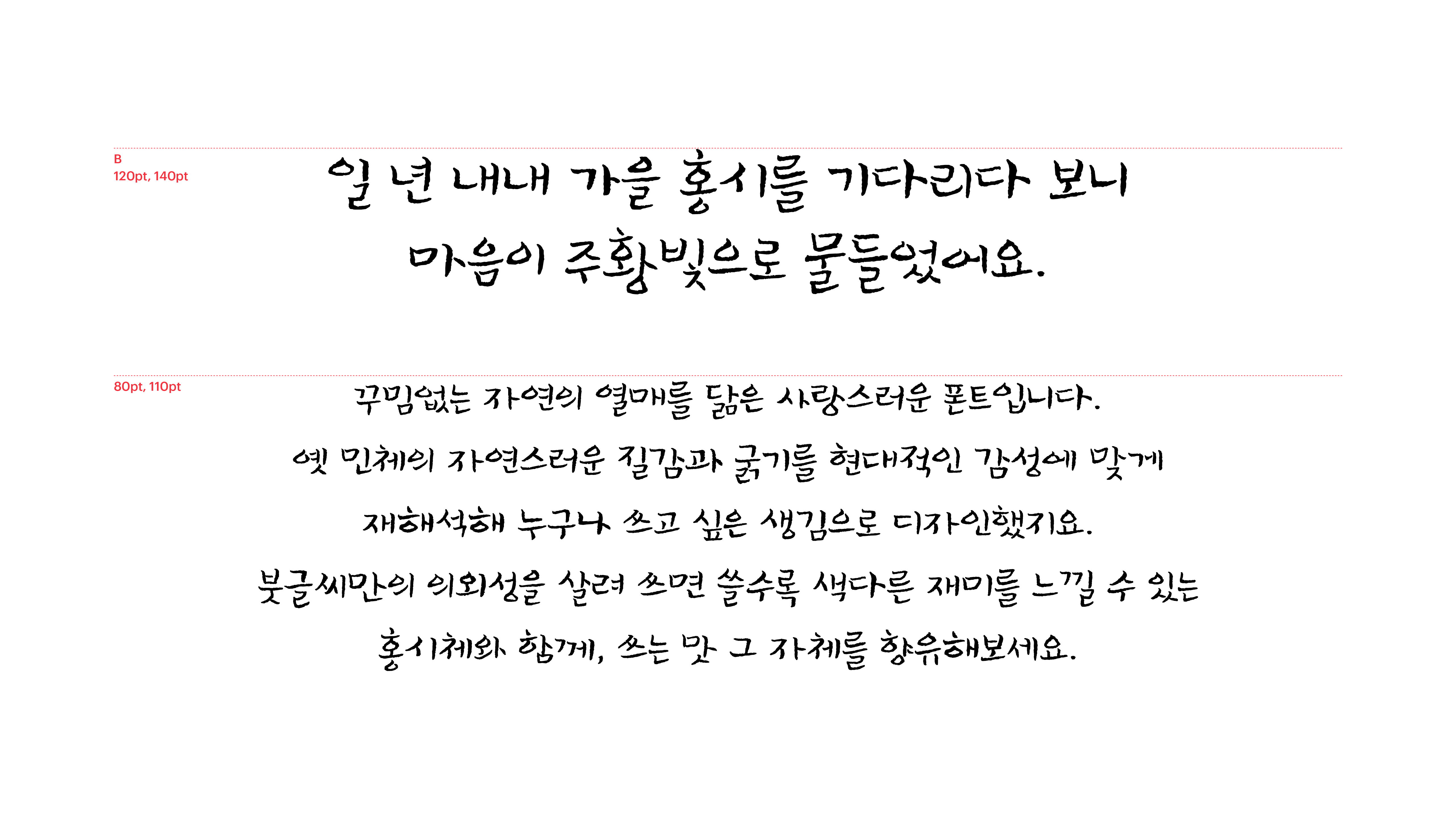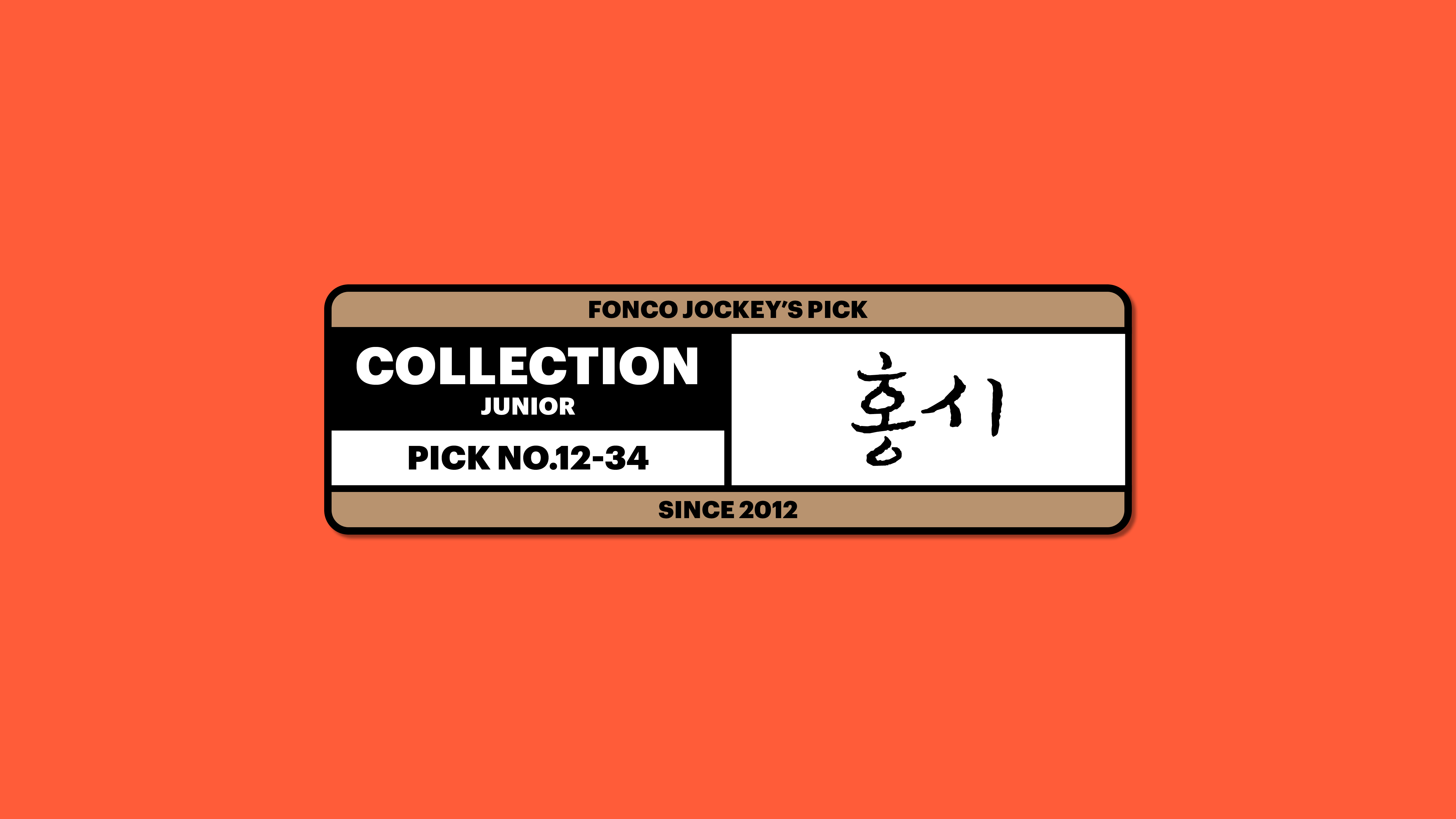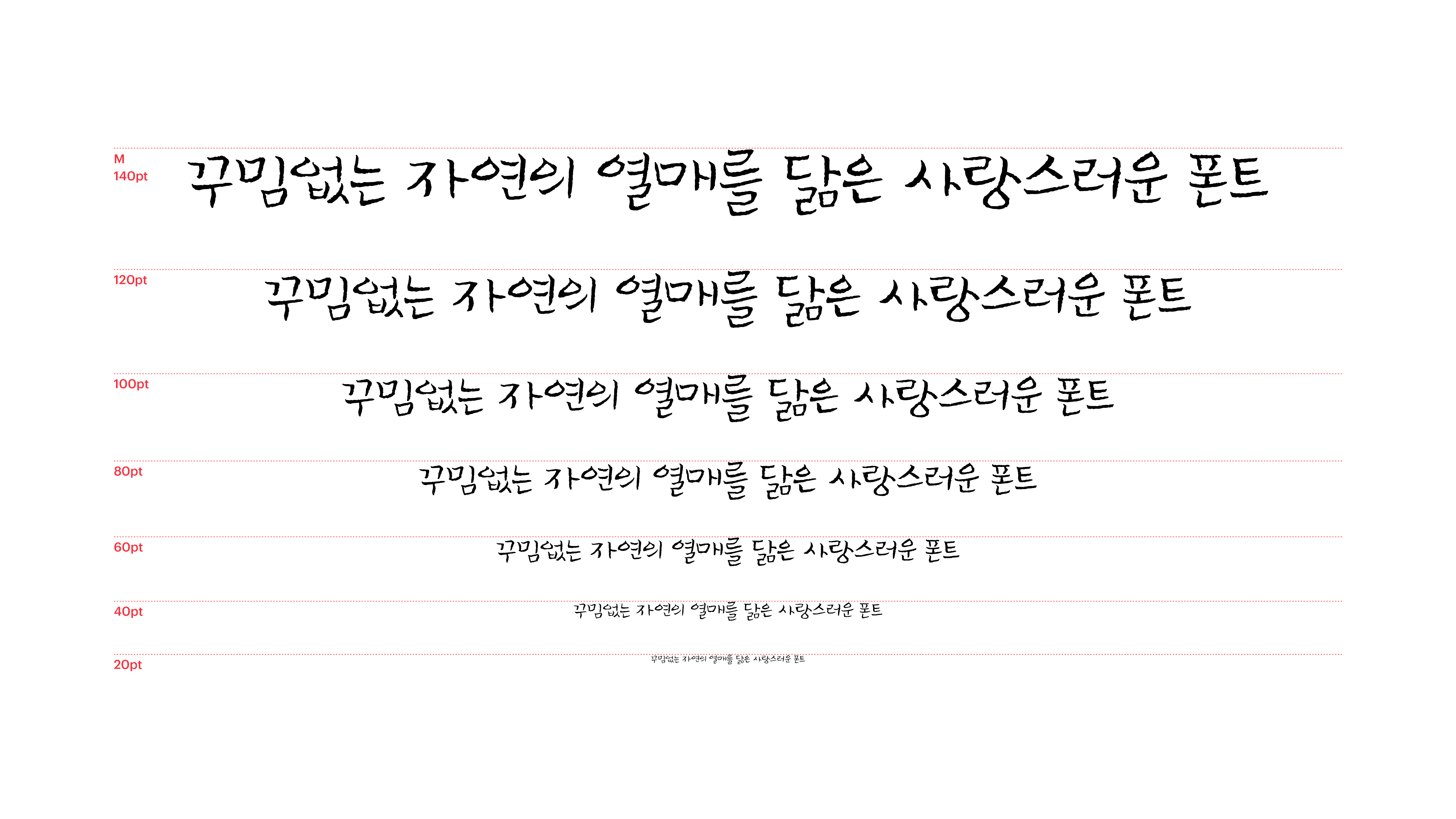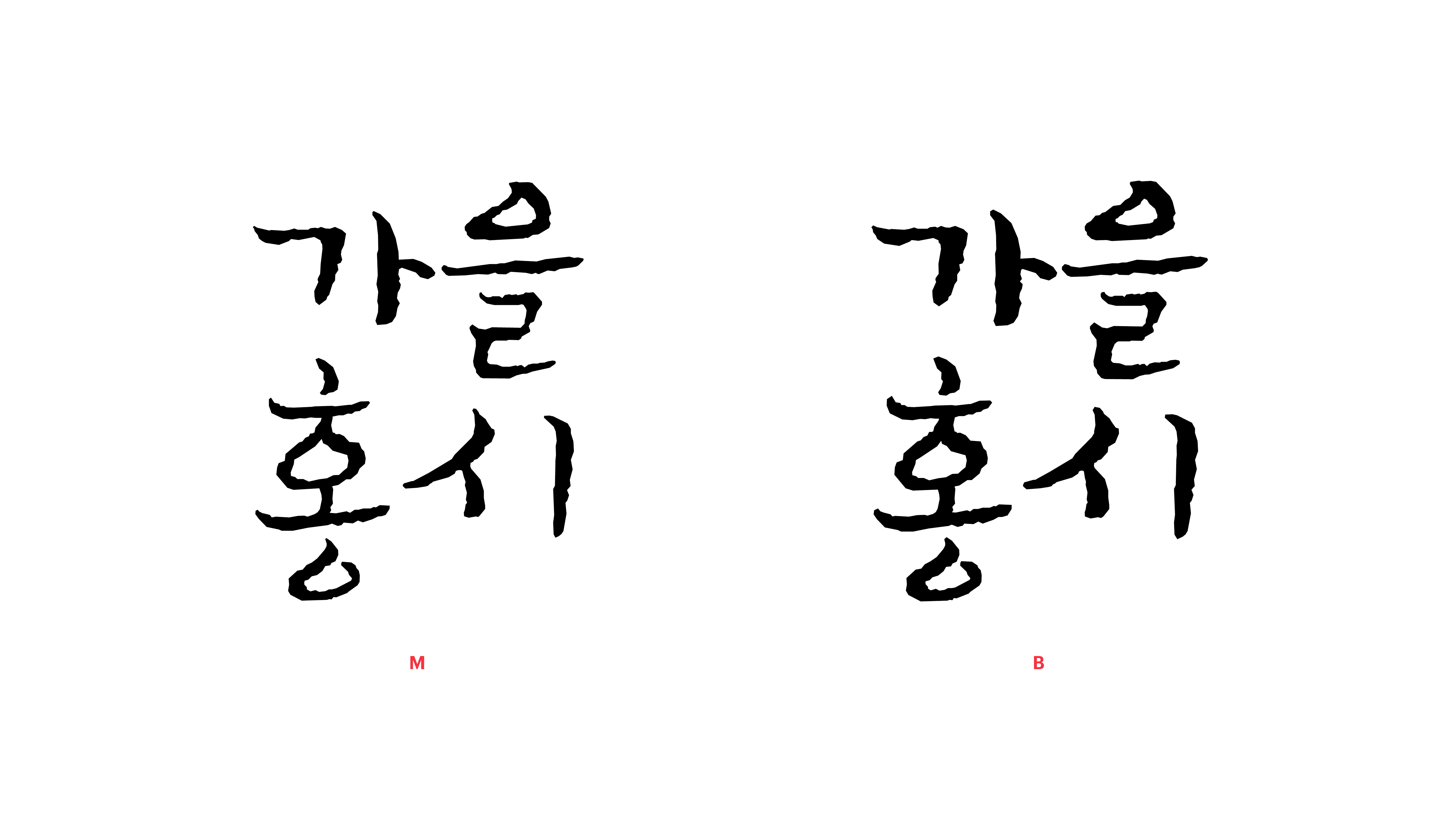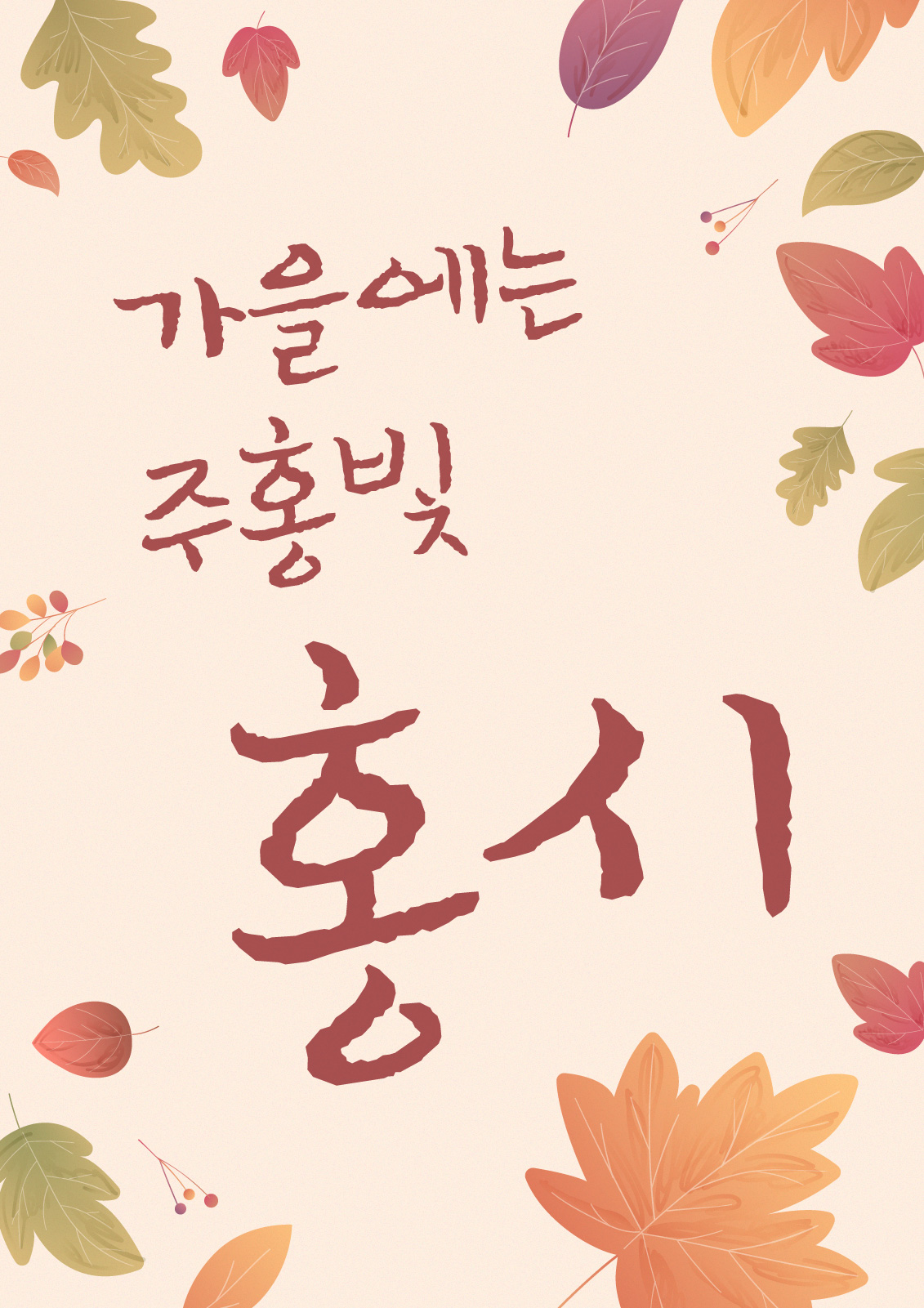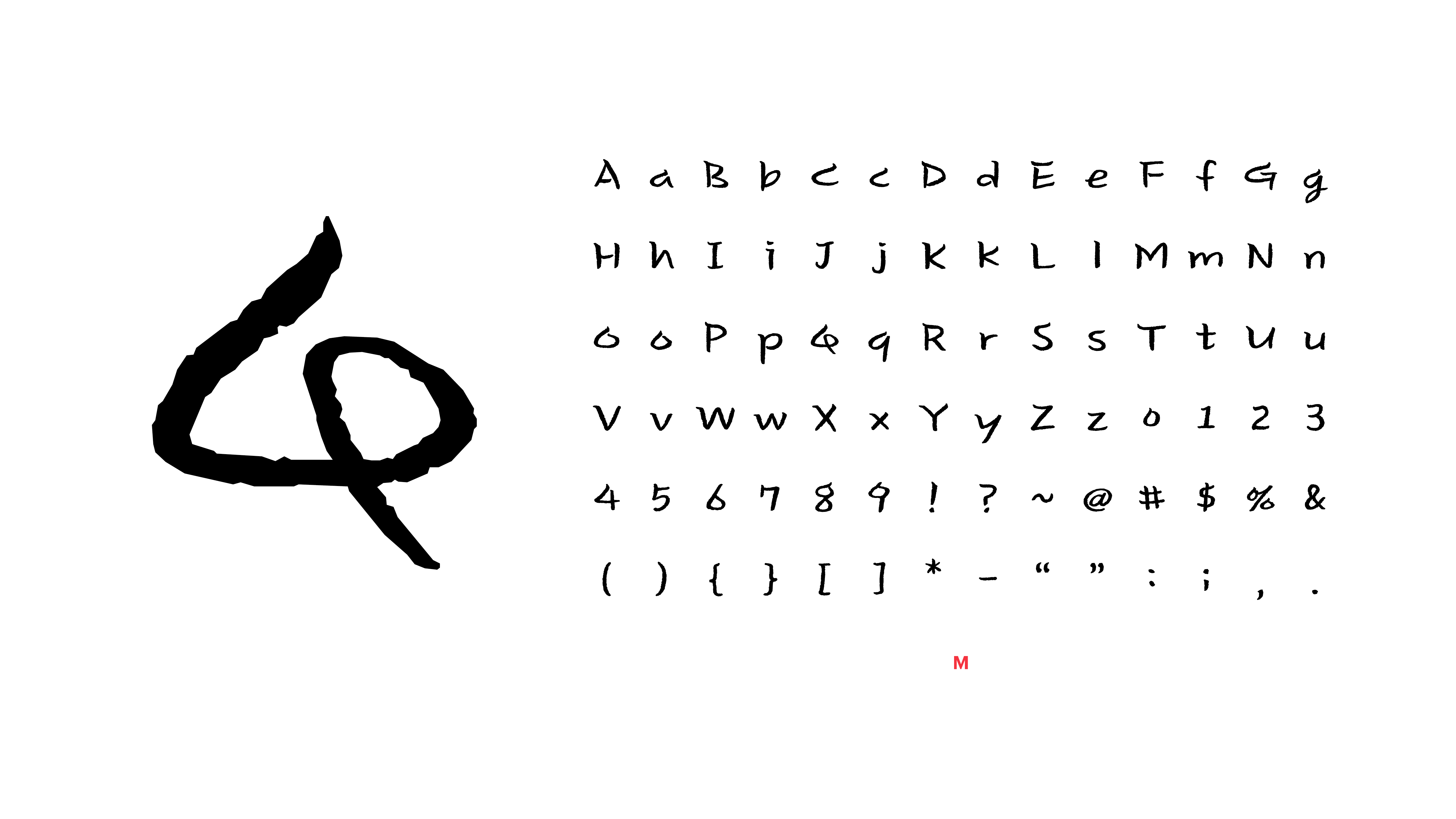
홍시
Yoon 홍시
꾸밈없는 자연의 열매를 닮은 사랑스러운 폰트입니다. 옛 민체의 자연스러운 질감과 굵기를 현대적인 감성에 맞게 재해석해 누구나 쓰고 싶은 생김으로 디자인했지요. 붓글씨만의 의외성을 살려 쓰면 쓸수록 색다른 재미를 느낄 수 있는 홍시체와 함께, 쓰는 맛 그 자체를 향유해보세요.